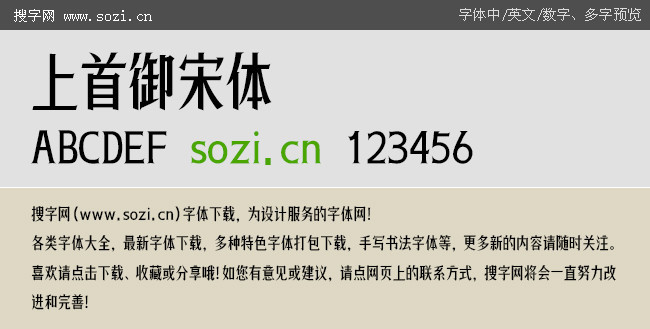
上首御宋體
搜字網(wǎng)給大家提供一款上首御宋體中文字體下載,上首御宋體字體筆畫融入了宋體的線條美感。筆畫采用橫細(xì)豎粗,點(diǎn)撇橫捺有尖角,一撇一捺都顯示出銳利之感且結(jié)構(gòu)緊密,整體添加了尖角處理使字體風(fēng)格偏銳利,適用于搭配標(biāo)志、廣告標(biāo)語、商業(yè)廣告等廣告設(shè)計(jì)。